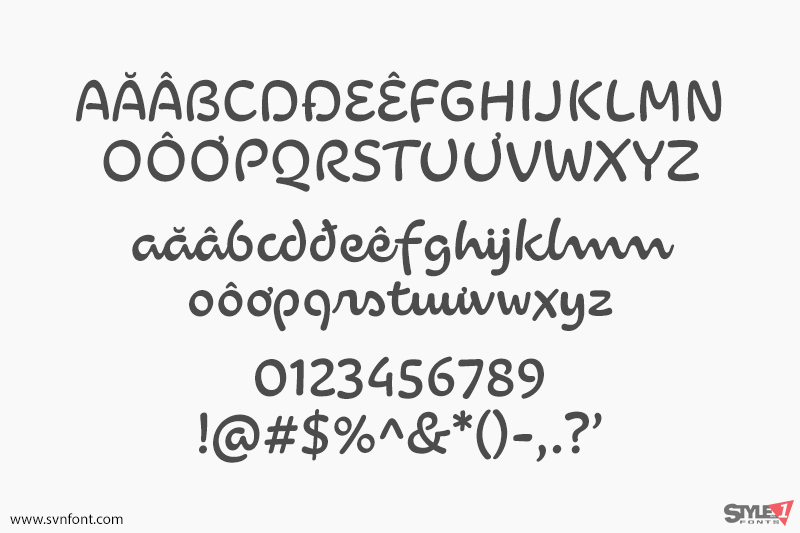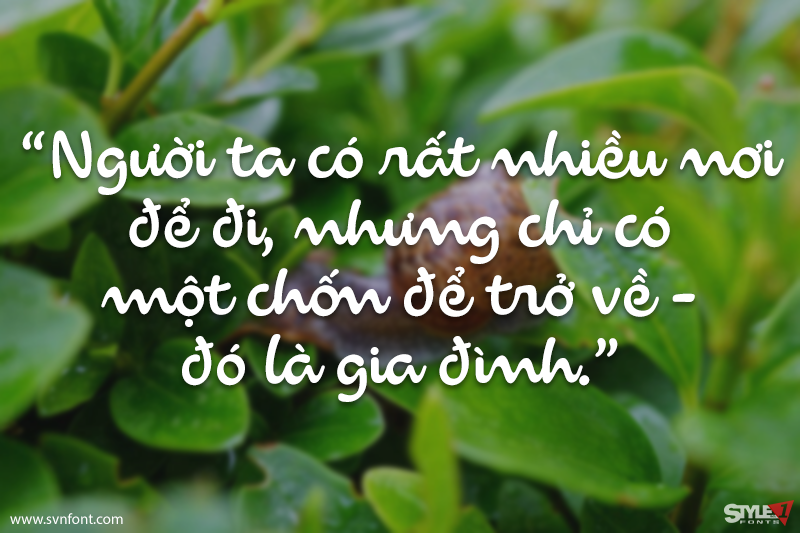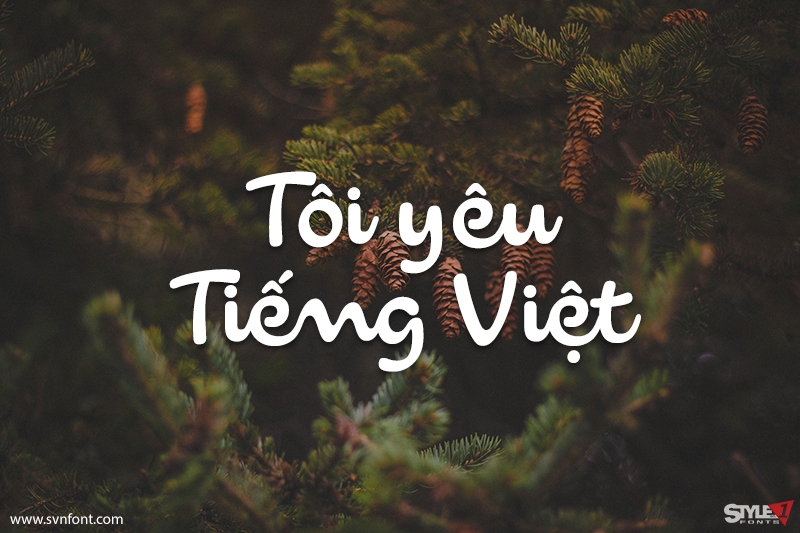
Rio 2016 là font chữ script tuyệt đẹp, font được sử dụng chính thức trong Thế vận hội mùa hè lần thứ XXXI – Rio 2016.
Nhà thiết kế: Bruno Maag
Nhà phát hành: Dalton Maag